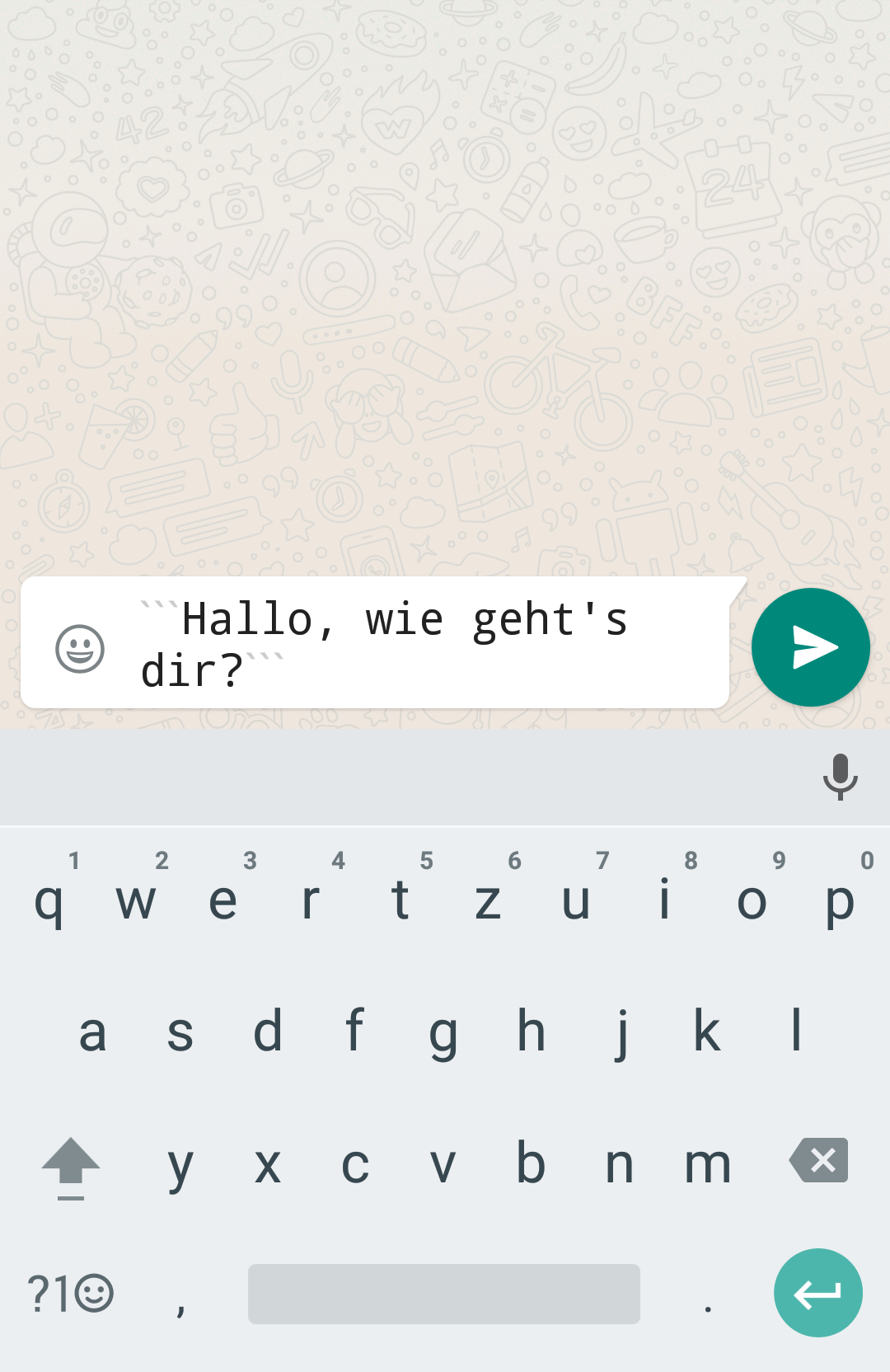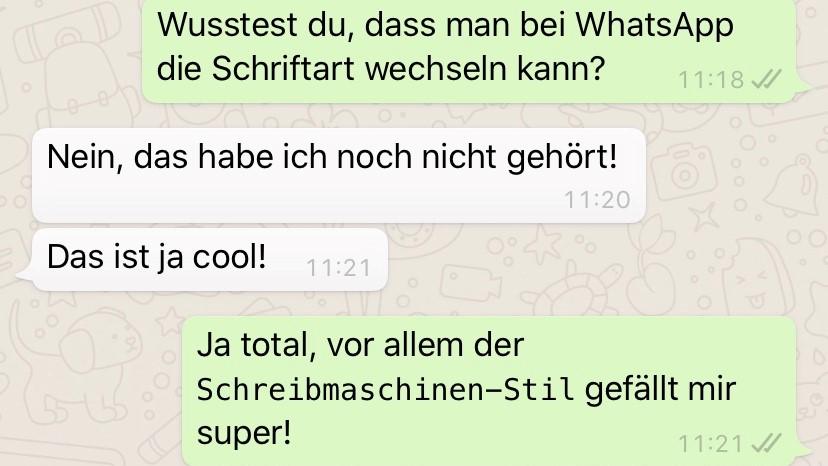
Schriftarten Whatsapp
Schriftarten whatsapp. Änderung der Schriftgröße Du kannst in den Einstellungen von WhatsApp die Schriftgröße in einem Chat in WhatsApp ändern Die Schriftgröße auf anderen Bildschirmen in der App basiert auf den Einstellungen deines Geräts. Want more ር̻ዐ̻ዐ̻ረ̻ ㄒ乇乂ㄒ ɛ̯ʄ̯ʄ̯ɛ̯ƈ̯ȶ̯ร̯, kaomojis ᕕ( ᐛ )ᕗ (҂⌣̀_⌣́) ʕ•ᴥ•ʔ, symbols ☬ and other cool fontchanging stuff?. Die Rubrik „Genutzte Schriftarten“ beinhaltet Posts über Schriftarten, die in Logos, Filmen, Büchern etc verwendet werden Die Rubrik „TextGenerator“ enthält einfache Tools, mit denen Sie Grafiken aus Schriftarten in verschiedenen Stilen und mit verschiedenen Texteffekten erstellen können.
WhatsApp Schriftarten ändern – so klappt‘s Whatsapp bietet seinen Nutzern nicht gerade eine umfangreiche Palette an Möglichkeiten, den verfassten Text zu formatieren Dennoch können Sie einige Spielereien mit dem Text in WhatsApp anstellen wie etwa Schriftwarten ändern. It is easy to share stylish fonts on WhatsApp You have to just click on the input section bar and type your text there It will generate your stylish fonts, then click on fancy text that you want to share This will copy your fancy text Now, you can able to paste and share stylish fonts on Whatsapp. ENGLISH Be very careful and take the time to read any terms & conditions before deciding to use the font commercially Ignorance is not an excuse for breaking the law.
Key Features • Stylish and creative fonts • Great variety of symbols • Emoji & Text emoji • Inspirational Quotes Template Fonts Fonts provides the most popular fonts which you can simply select in the keyboard cursive, gothic, bold, italic, upside down, bubble, and so much more!. Monospaced fonts are ideal for hackers, coders and the lovers of ASCII art, insisting on a font set with a fixed character width for absolute symmetry. Looking for Android fonts?.
WhatsApp verwendet die Textgröße, die du in den Einstellungen deines iPhones ausgewählt hast So passt du die Textgröße von Nachrichten in WhatsApp an Öffne die iPhoneEinstellungen > Tippe auf Anzeige & Helligkeit > Textgröße Schiebe den Regler, bis die gewünschte Größe erreicht ist Hinweis Wenn du Größerer dynamischer Text in. Solved Guten , wie kann ich Adobe fonts so einstellen das ich es in WhatsApp oder anderen Apps verwenden kann?. 100 ℭ𝔬𝔬𝔩 & 𝓈𝓉𝓎𝓁𝒾𝓈𝒽 Fancy Font Generator with Copy and Paste Cool 𝐹𝒶𝓃𝒸𝓎 𝒯𝑒𝓍𝓉 Symbols Different Calligraphy Font Generator Copy and Paste Cute Fancy Fonts and Letters, Pretty Fonts, Lingojam Fancy Text, Gothic Font, Fancy Word Generator, Curcive Font Generator.
This is a Aesthetic Text Generator that you can use to make fonts for Instagram, Tumblr, Twitter, Facebook, Discord, TikTok, etc Convert any Normal text into Aesthetic Text using our font changer Get the cool Aesthetic symbols and copy and paste them to make your bio unique. Aesthetic font generator tool will let you convert simple and normal font style into your desired font Simply type or copy the normal text into the blank text field. You can use these symbols at various social media platforms such as Facebook, Whatsapp, Twitter, Instagram, etc for commenting, messaging, bio and status update These symbols will make texts look more attractive One click copy and paste options.
Fixedsys Wie Ihr Die Versteckte Schriftart In Whatsapp Aktiviert
Whatsapp Schriftart Andern So Geht S Chip
Whatsapp Tipp Andere Schriftart In Einer Nachricht Androidmag
So Schreiben Sie Stilvolle Whatsapp Nachrichten